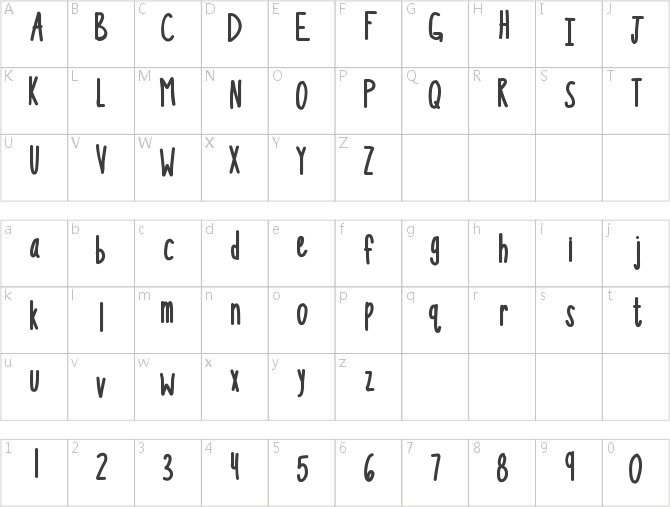
KBSoThinterestingBold 詳情頁
KBSoThinterestingBold字體字庫是一款讓人賞心悅目、百看不厭的英文字體,適合各類廣告和產(chǎn)品包裝設(shè)計應(yīng)用,字體大小0.02MB,格式為ttf字體,上傳用戶是東方時尚,作者/版權(quán)方為未知